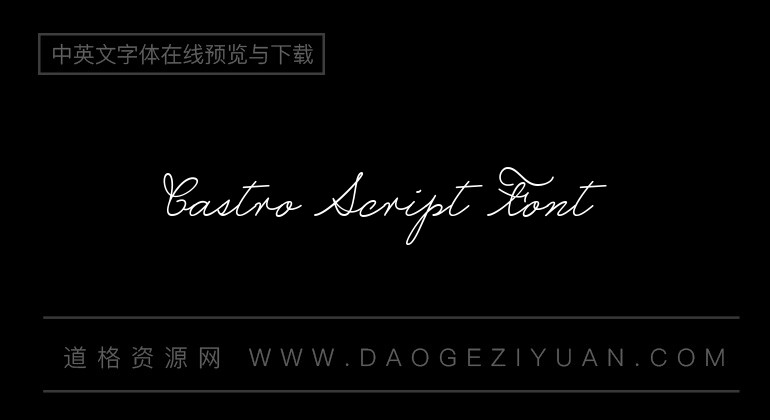
Castro Script Font
Castro Script Font 是一款优美的手写字体,其特点是笔画流畅、圆润且具有一定的装饰性。该字体的设计灵感来自于传统的手写艺术,其字形呈现出一种自然、有机的感觉,适用于各种文本设计场景,如印刷品、海报、标志等等。 Castro Script Font 字体具有多种字重,包括 Regular、Bold、Italic 等,可以满足不同文本设计的需求。此外,该字体还包含了多种字形和特殊字符,如花卉图案、箭头、星形等等,为设计师提供了更多的创意空间。 总的来说,Castro Script Font 字体是一款漂亮、实用的手写字体,其独特的设计风格和丰富的字形与特殊字符,使其成为许多设计师的首选字体之一。
Castro Script Font是一款非常不错的手写艺术字体,具有很好的视觉感,适合于文化类的宣传设计、商业类品牌的广告和产品包装设计以及个性化文字排版等较多场景。